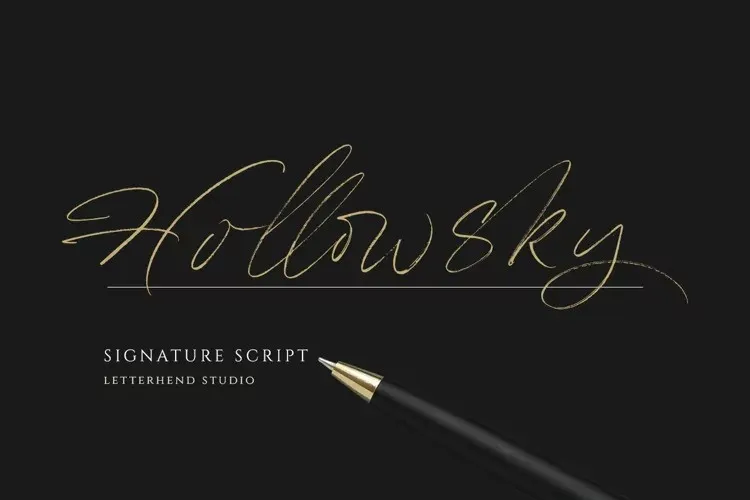
A Hohlsky Font é uma escolha perfeita para designers que procuram uma tipografia com um toque artesanal e elegante. Com estilo único, alternativas estilísticas, ligaturas e textura áspera, ela transmite a sensação de escrever à mão em vez de usar um tipo digital. Esta fonte é especialmente adaptada para aplicações como logotipos, cartões de convite, rótulos, logos, revistas, livros, cartões de casamento e embalagens. Também se destaca em setores variados, incluindo moda, maquiagem, material de escritório, literatura e anúncios. O seu design limpo e sofisticado oferece um aspecto atraente que pode ser usado para qualquer finalidade, tornando-a uma fonte indispensável para designers amadores e profissionais.